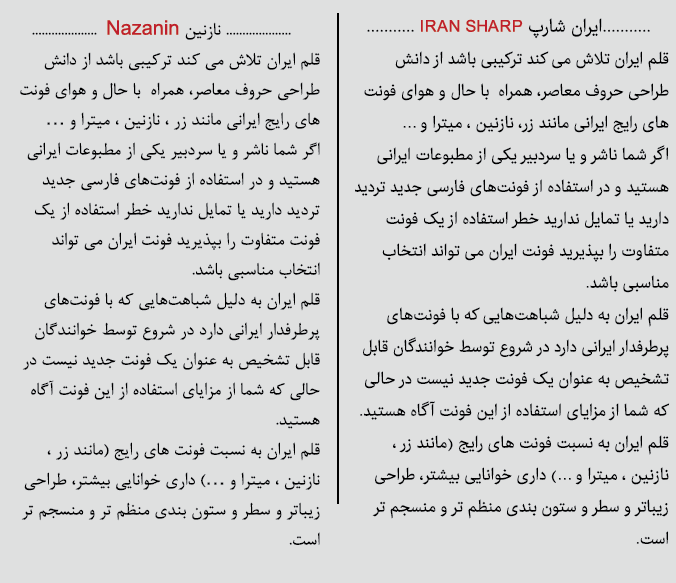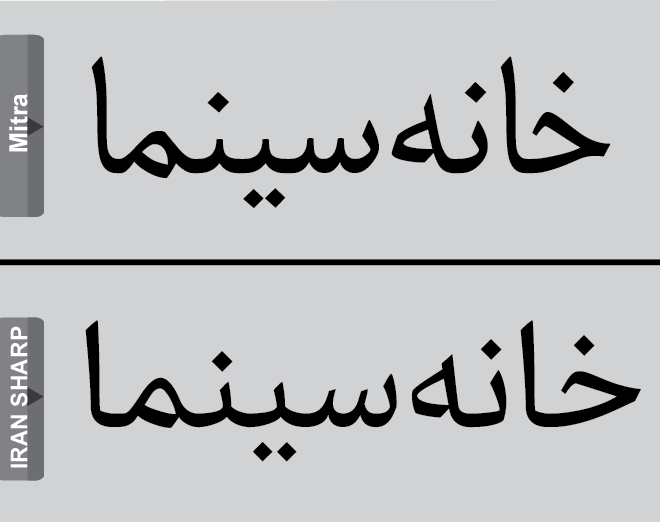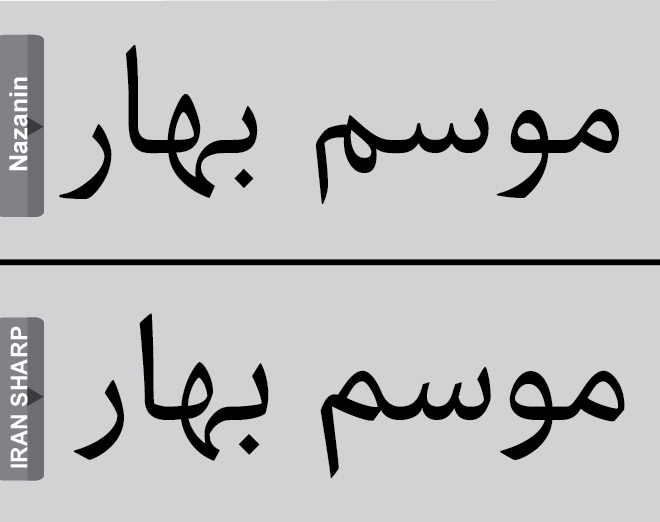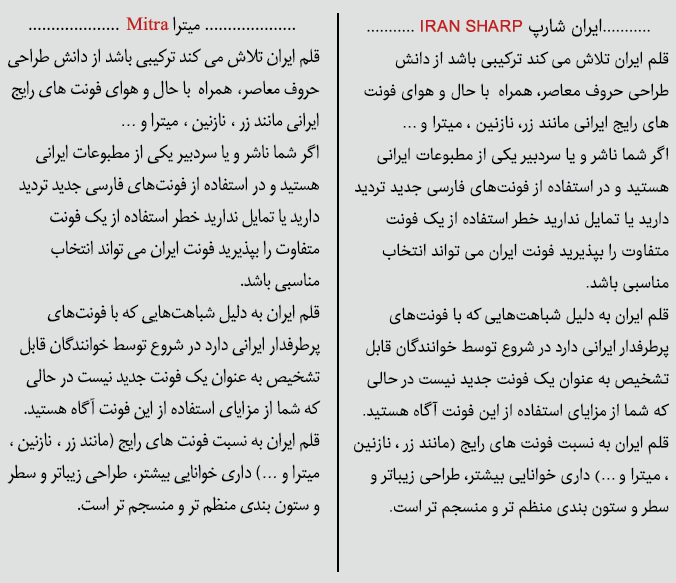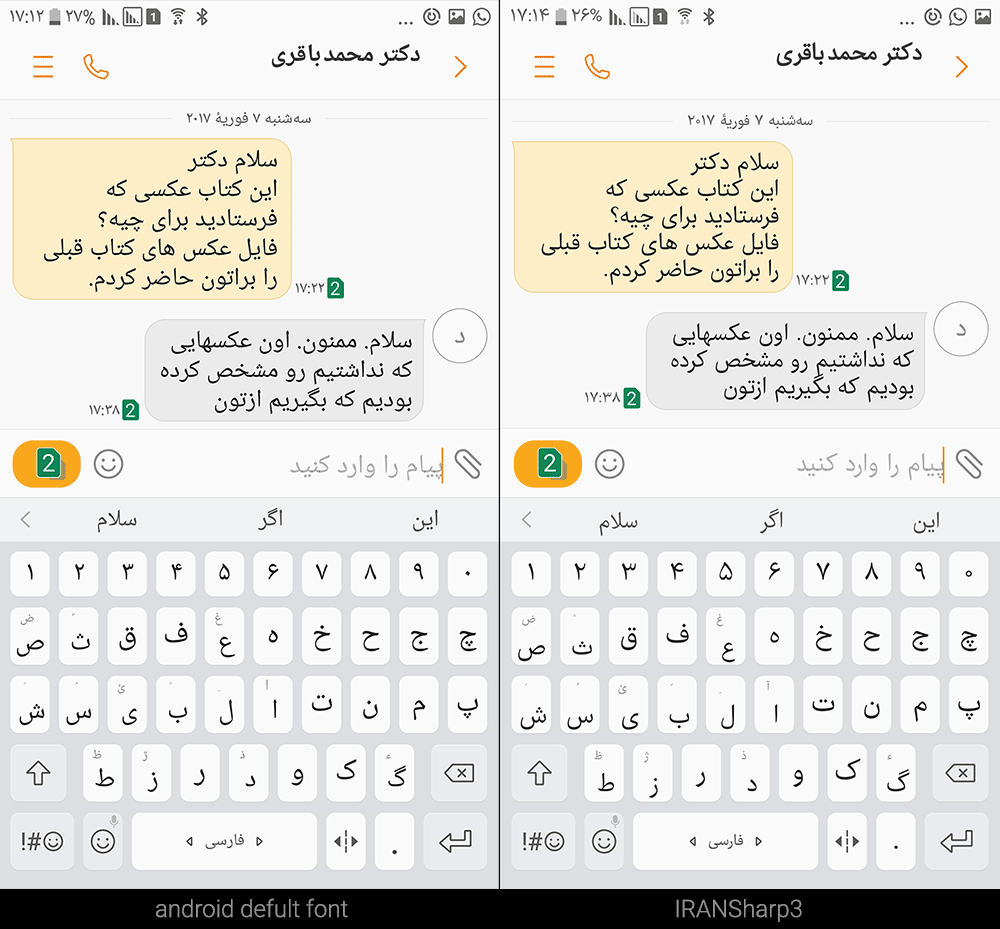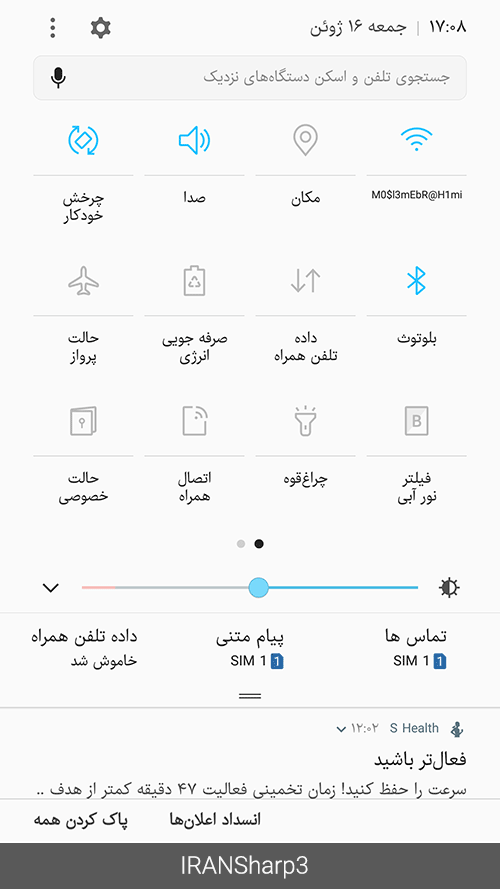
- موبایلفونت: فونتهای این دسته با توجه به سایز و فشردگی محیط موبایل تنظیم شده اند.
- فونت چاپ: اندازه این دسته فونت مشابه فونتهای قدیمی مرسوم در صفحه آرایی تنظیم شده است تا طراحان مطبوعات بتوانند با همان تنظیمات حروفچینی کنند.
- علایم و اعداد فارسی: در این بسته فونتها هم به صورت استاندارد و هم با اعداد تمام فارسی موجود هستند و شما برای فارسی سازی اعداد هیچ مشکلی نخواهید داشت.
در این مجموعه فونت برای نخستین بار در فونت فارسی می توانید هماهنگی ۱۰۰٪ وزنها را تجربه کنید. بدین صورت که با تغییر وزن فونت حروف و پاراگراف حتی یک پیکسل از جای خود حرکت نمیکند و شما بدون هراس از جابجایی صفحه بندی خود می توانید وزن فونت را کم یا زیاد کنید.
پیشنهاد میکنیم فونت ایران شارپ را در مقایسه با فونتهای مشابه ببینید و قضاوت کنید کدام فونتخواناتر است و در پاراگراف انسجام بیشتری دارد: